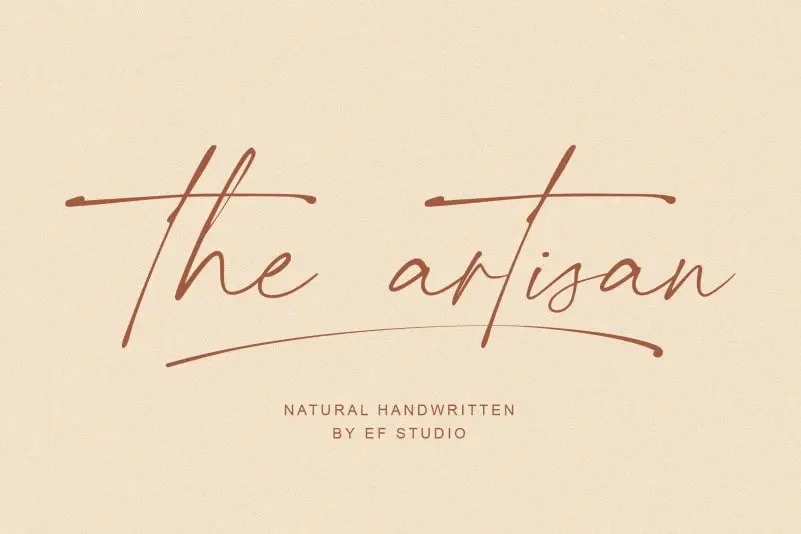
The Artisan Handwritten Font – Download Grátis
A fonte “The Artisan Handwritten” é uma escolha perfeita para quem deseja adicionar um toque especial aos seus projetos visuais. Ela foi criada pelo font designer Ef Studio, apresentando linhas suaves e traços delicados que imprimem em qualquer design. Além disso, possui ligaturas adicionais e swashes, tornando-a ainda mais versátil e atraente para uma variedade de usos, desde o branding até o design de logotipos, impressão em mercadorias, websites, mensagens personalizadas ou publicações nas redes sociais. O uso deste fonte é simplificado, permitindo que você personalize seu design de forma criativa e moderna. A combinação única desta fonte traz um toque artístico e único a qualquer projeto, tornando-a uma opção ideal para quem busca adicionar personalidade ao seu trabalho. Com “The Artisan Handwritten”, as suas criações se destacam em uma maneira singular, garantindo que seus trabalhos saiam do convencional e entram no universo dos design exclusivos e criativos.